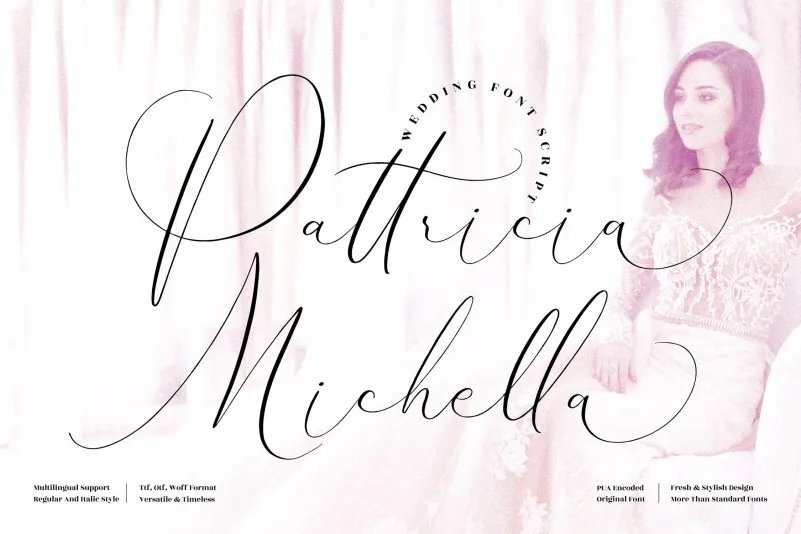
A fonte “Pattricia Michella” é uma elegante caligrafia perfeita para qualquer projeto que exija um toque refinado de texto bonito. Suave e romântica, ela se adapta perfeitamente a múltiplas categorias, como identidade visual, design de móveis de casa, embalagens de produtos, t-shirts, capas de livros, cartões de nome, convites e cartões de agradecimento. Além disso, é perfeita para tags, marca d’água em fotografias, eventos especiais e qualquer outro trabalho que precise de um gostinho de escrita bonita. Seja você um designer gráfico, criador de produtos ou simplesmente alguém que gosta de incluir elementos estéticos em seus projetos pessoais, “Pattricia Michella” é uma escolha perfeita para tornar seu trabalho ainda mais especial.